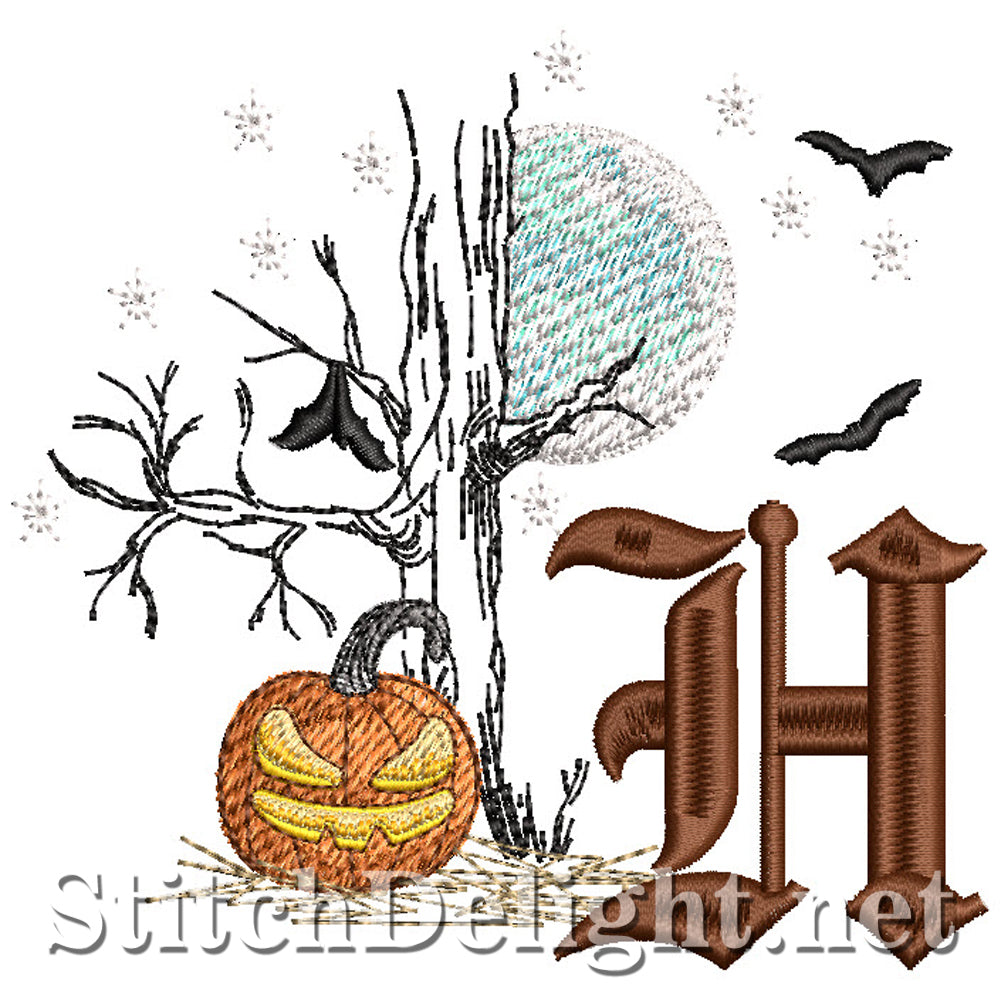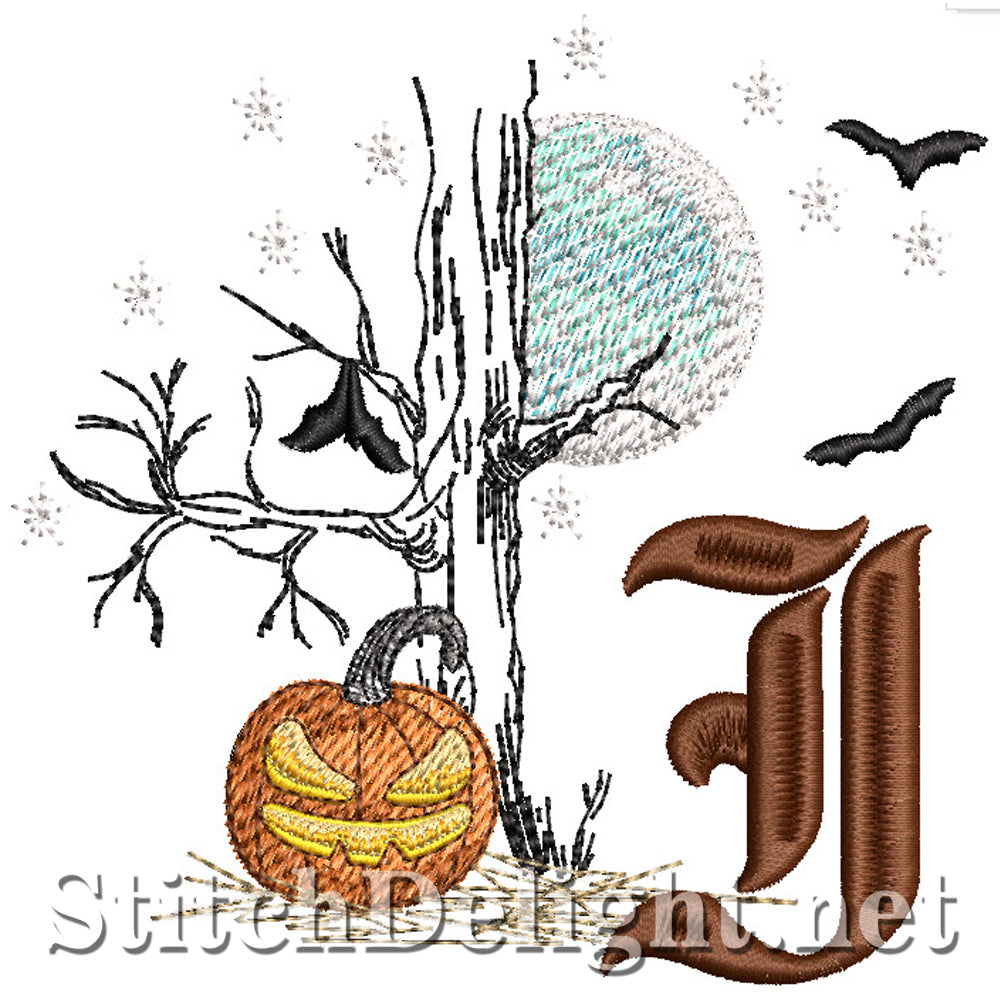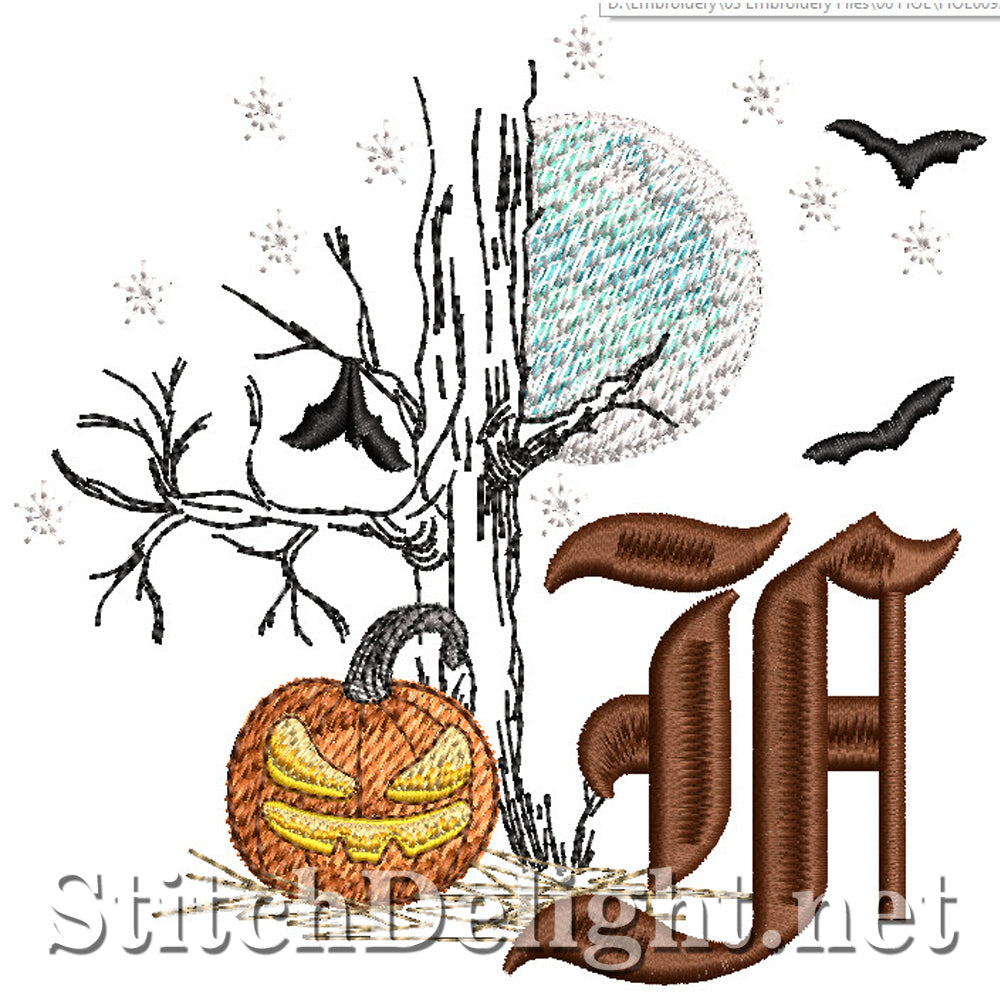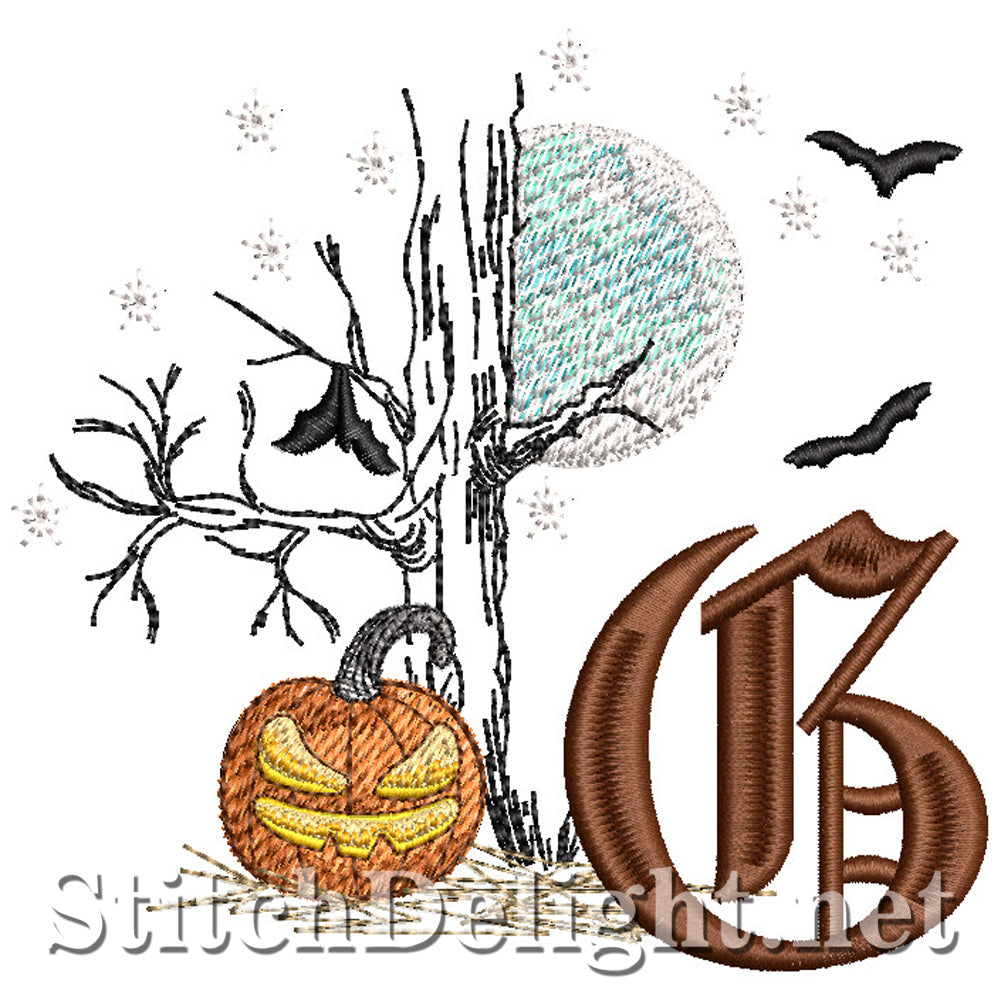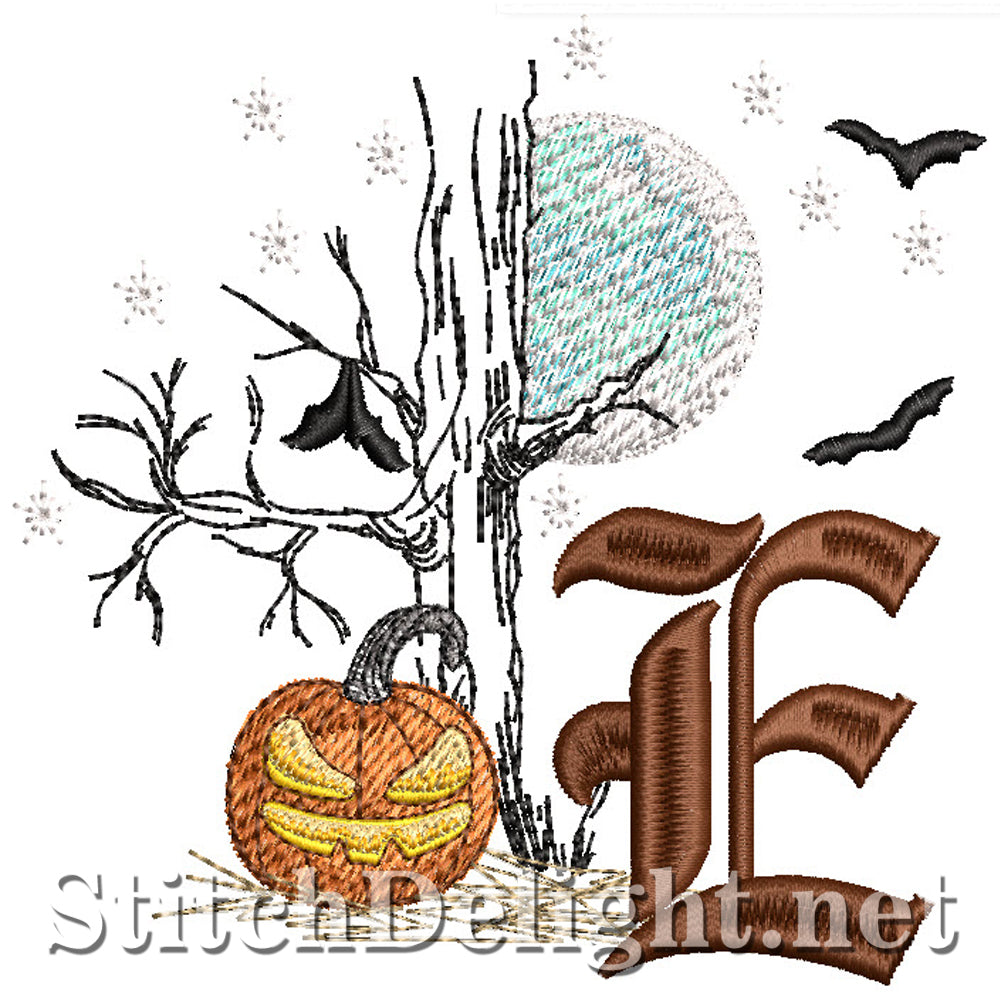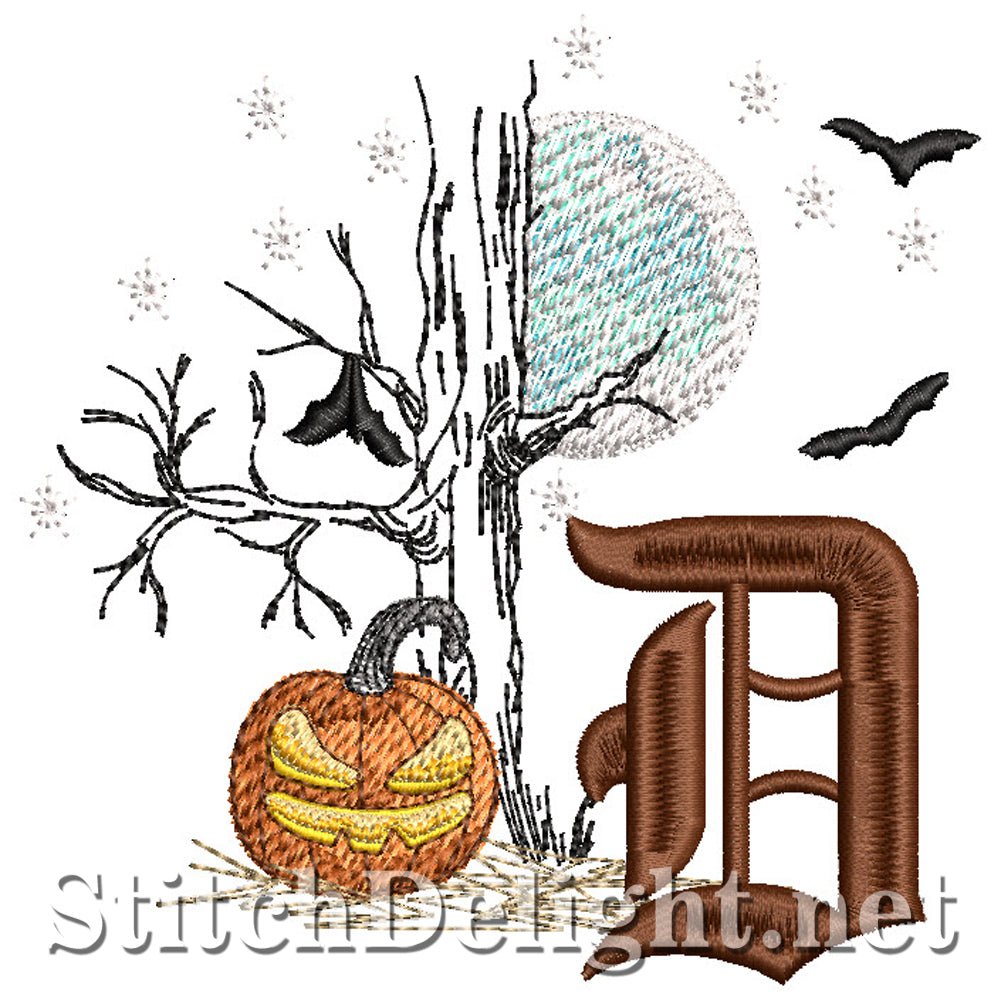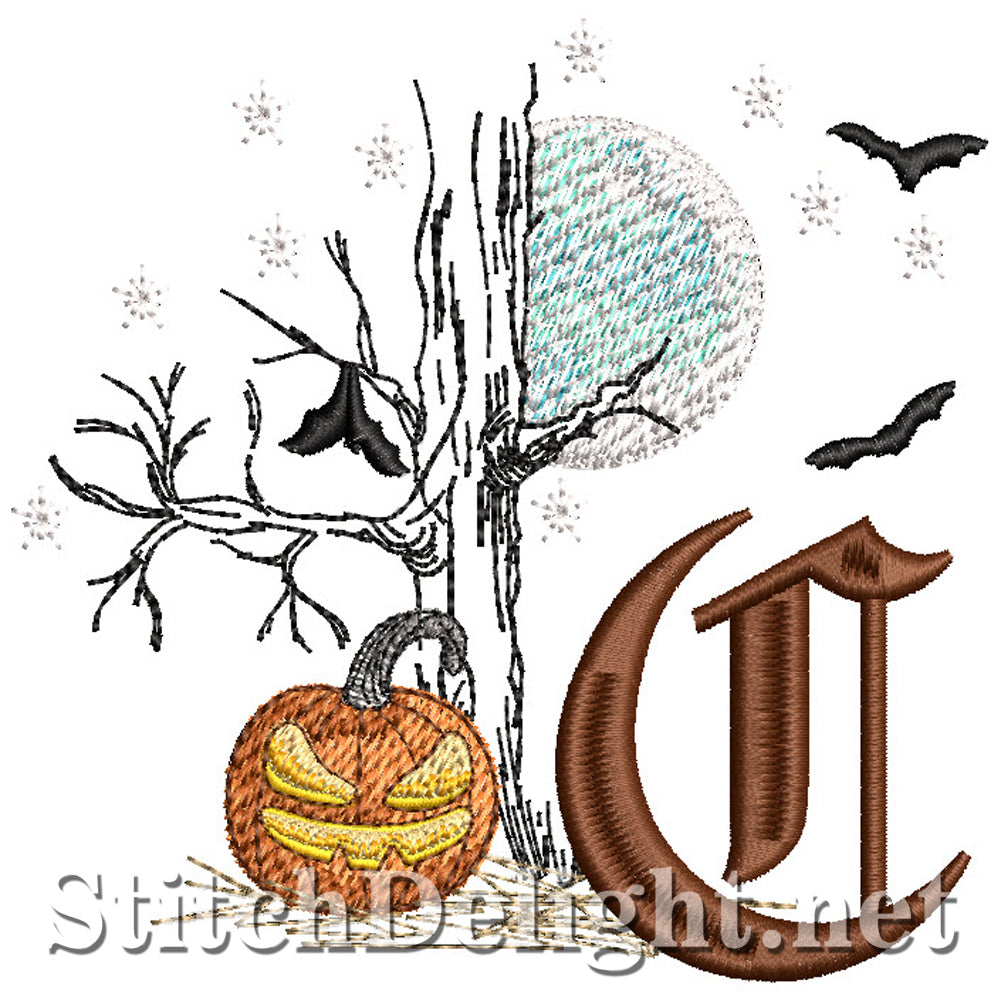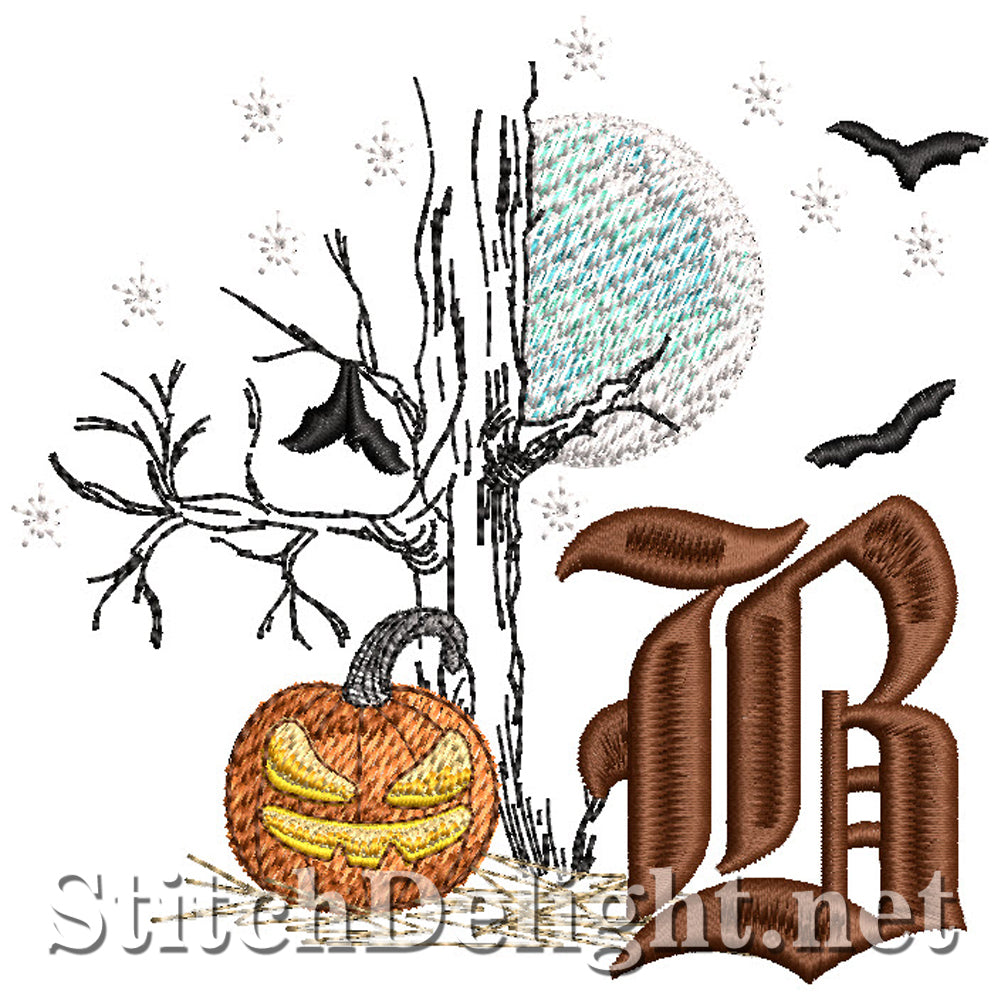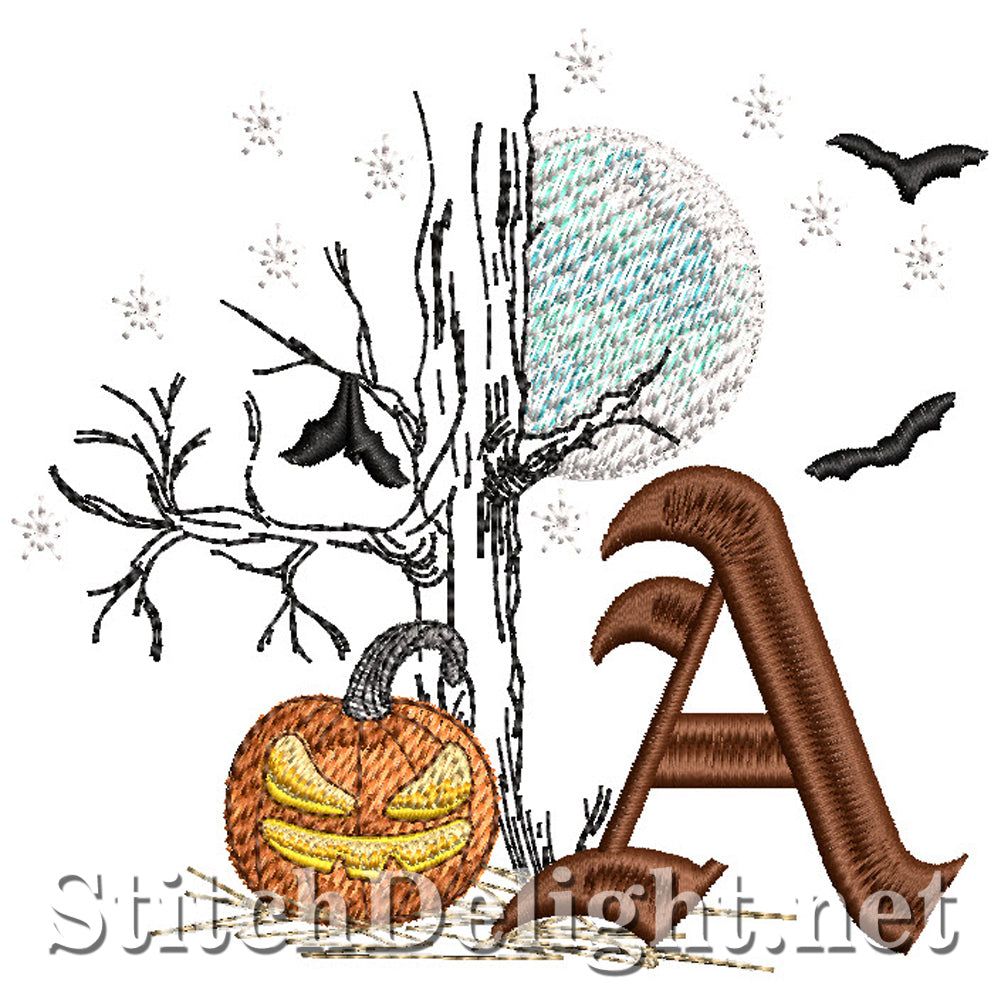
Une police effrayante parfaite pour tout projet d'Halloween ou amateur de monstres. Cette police effrayante est compatible avec les tailles de cercle 4x4 et plus ! La police correspondante est HOE0094 Ancient Typography, recherchez simplement HOE0094 ;)